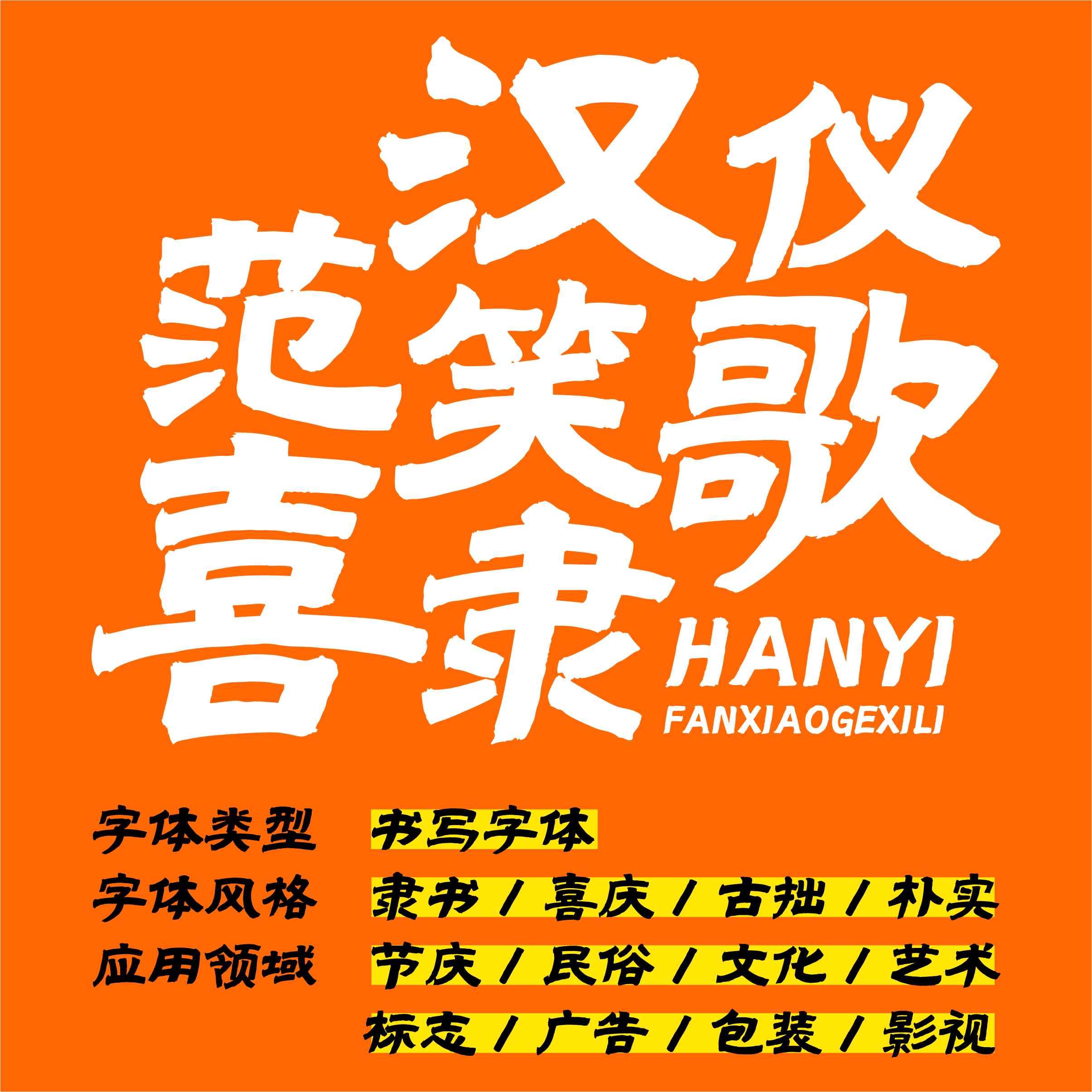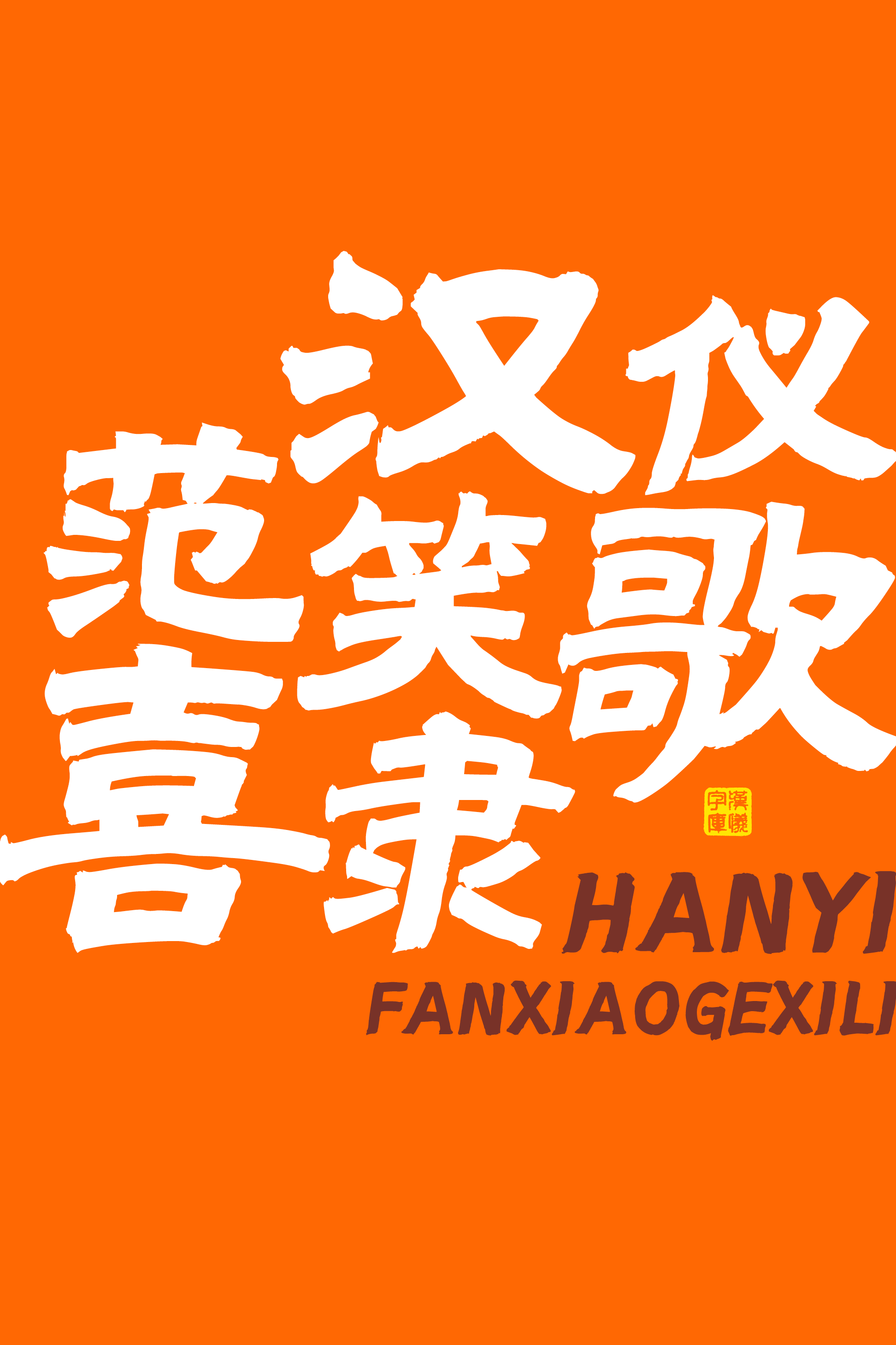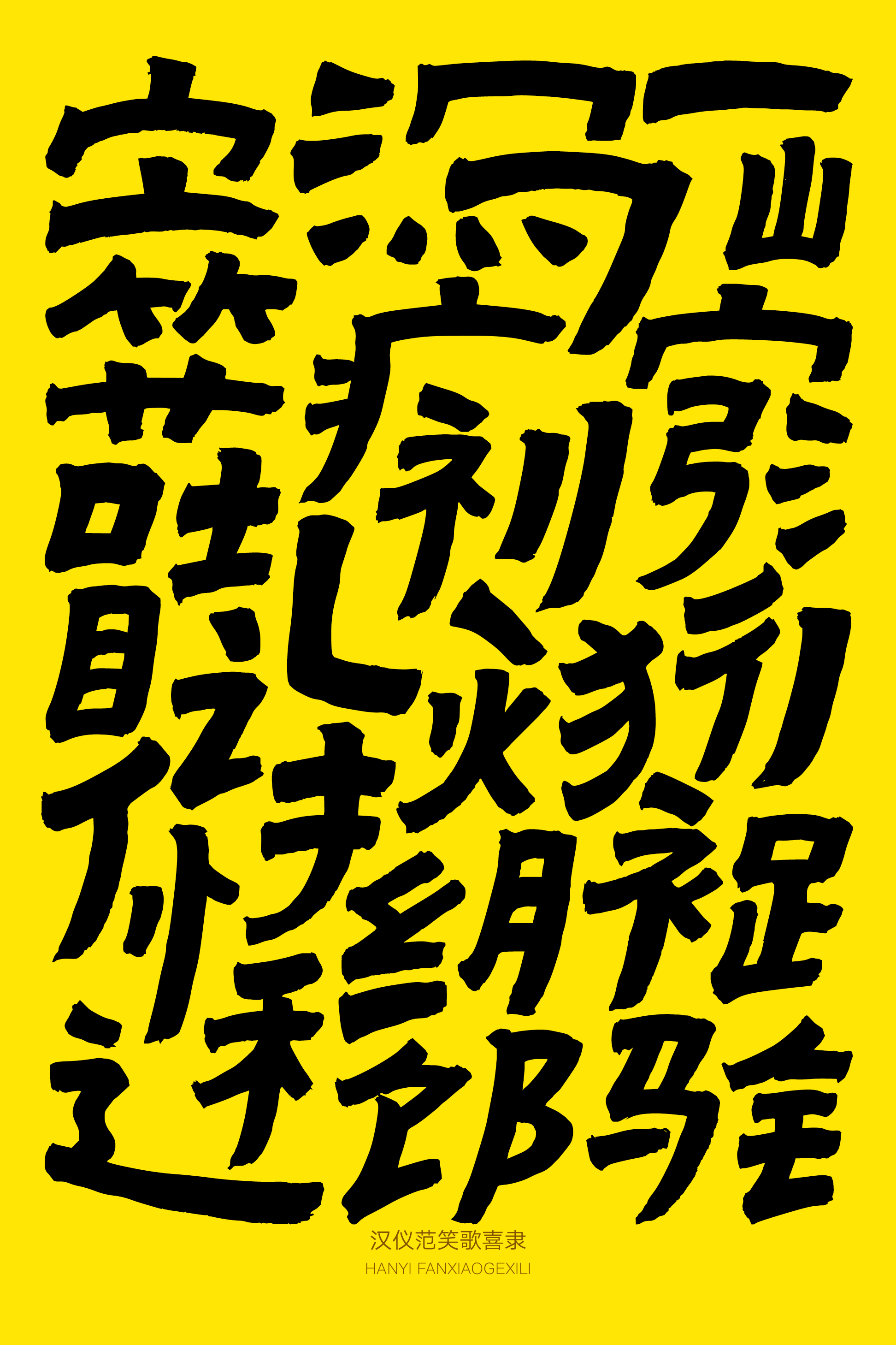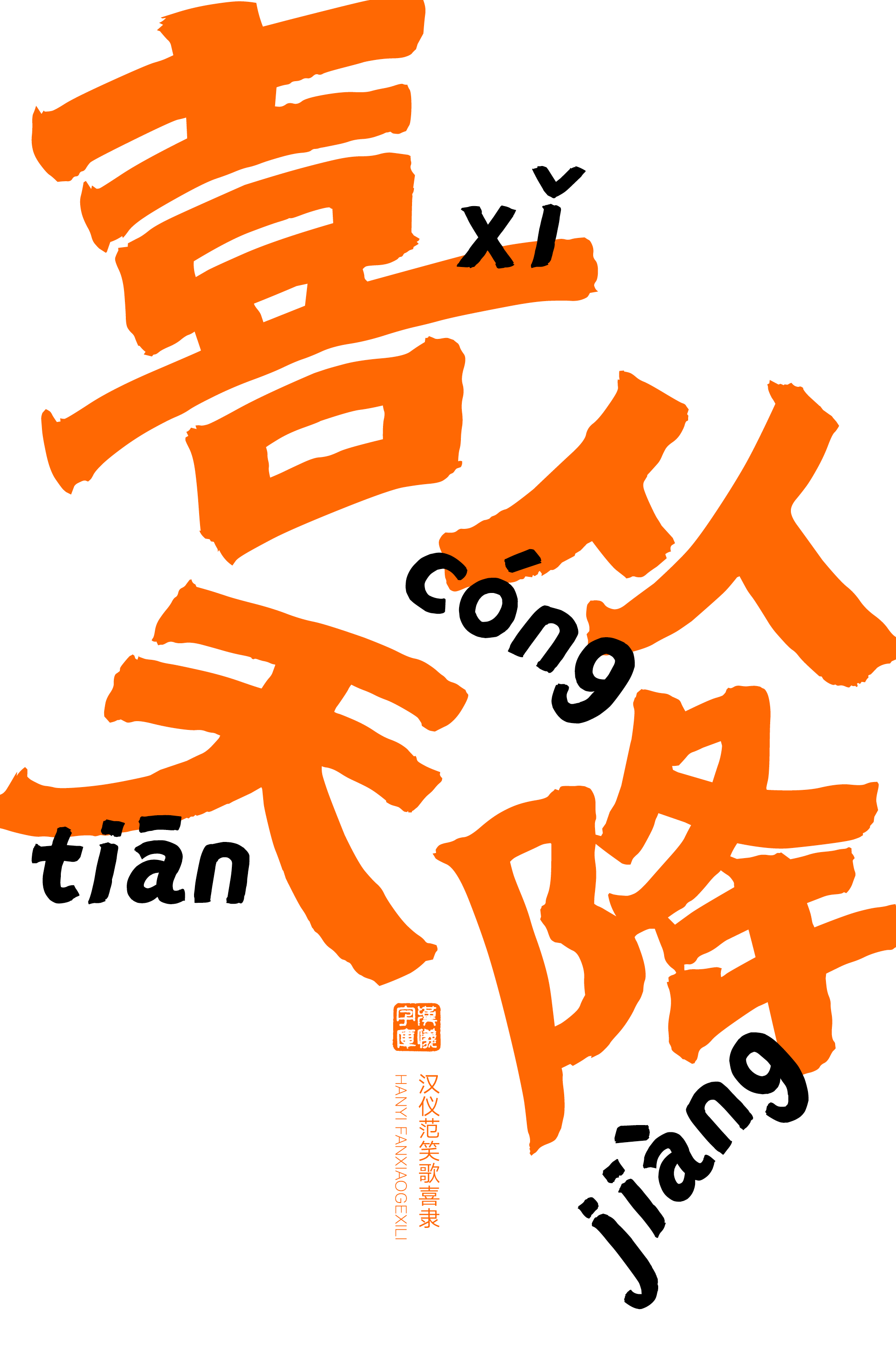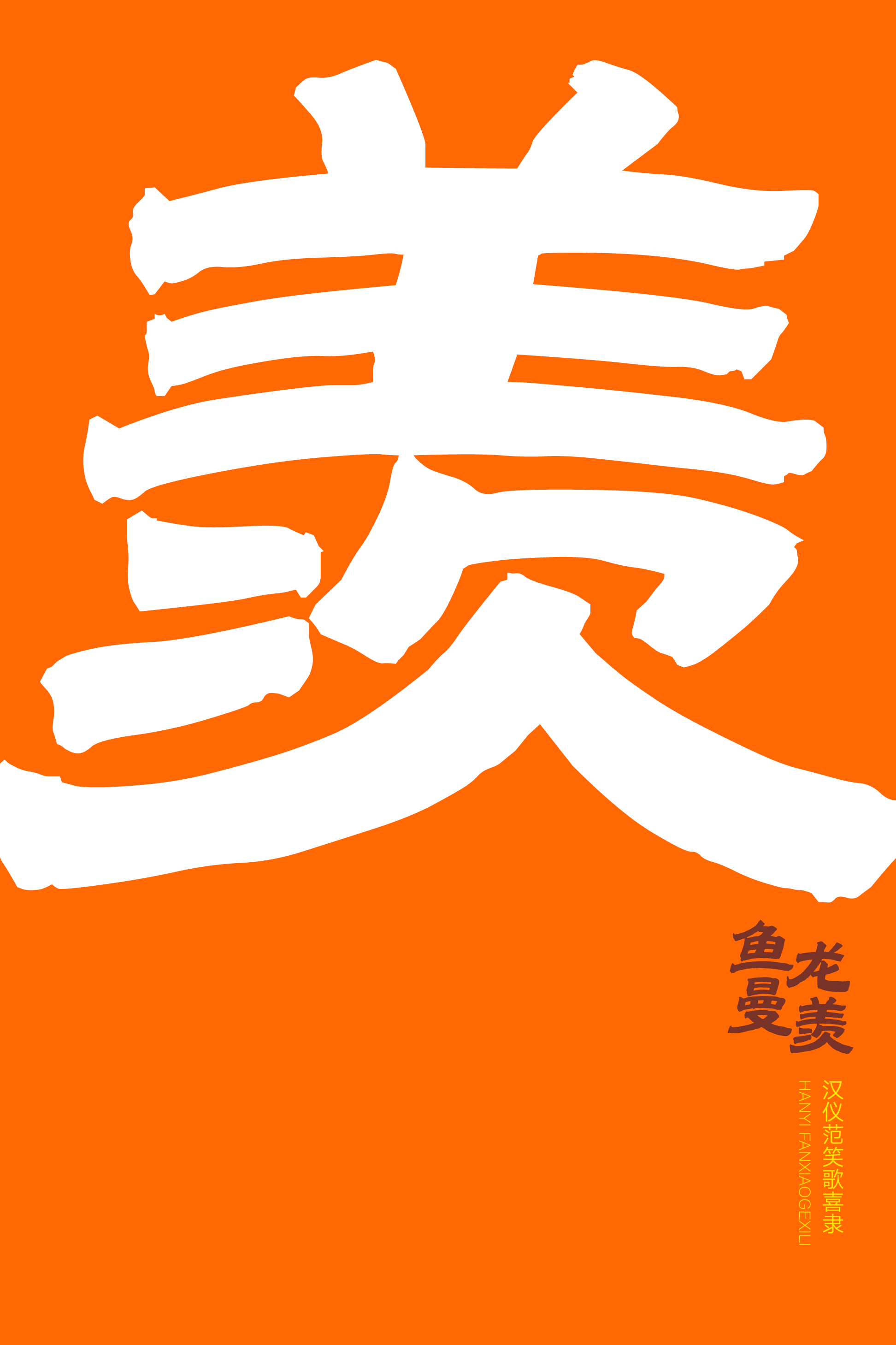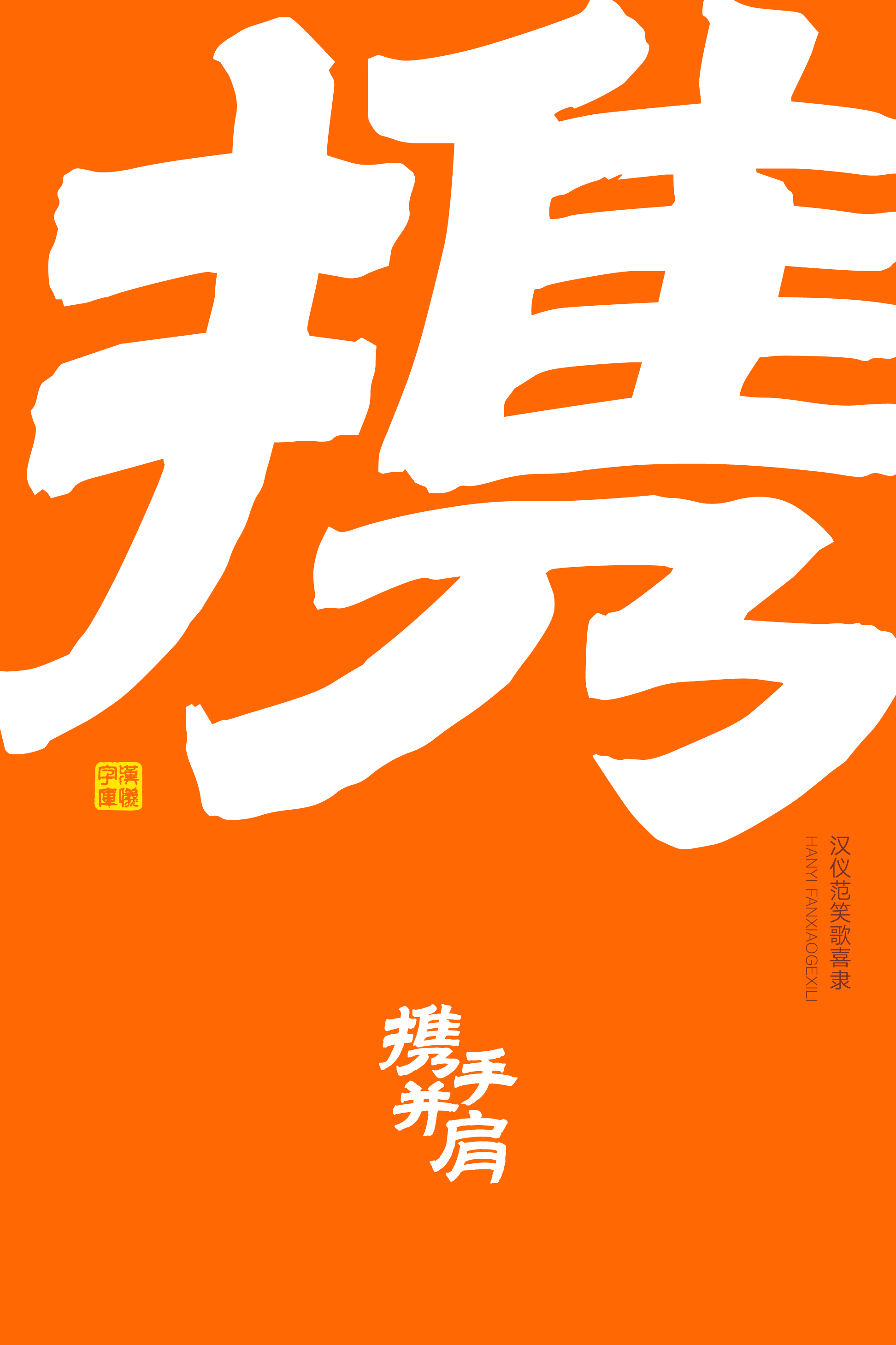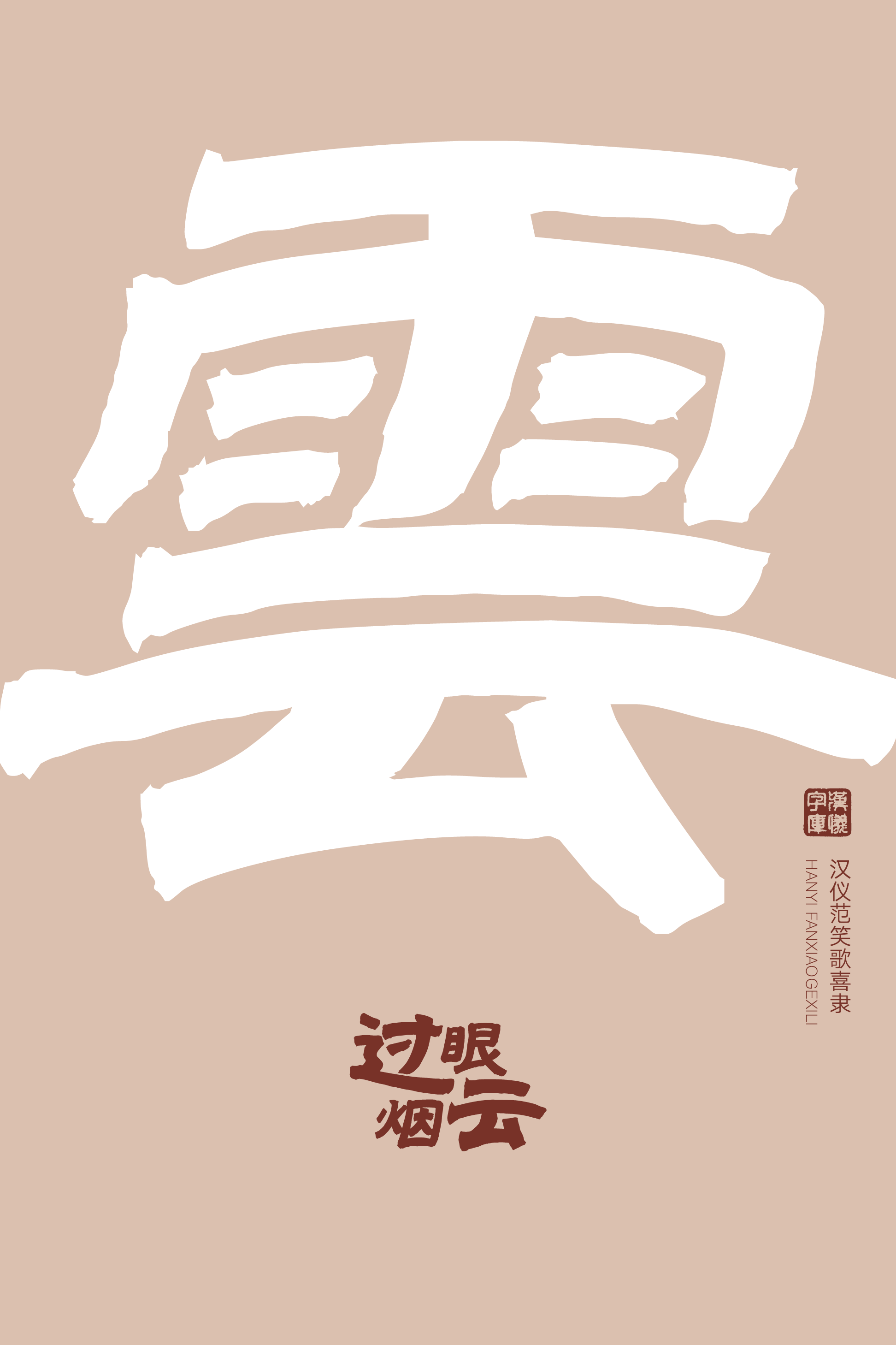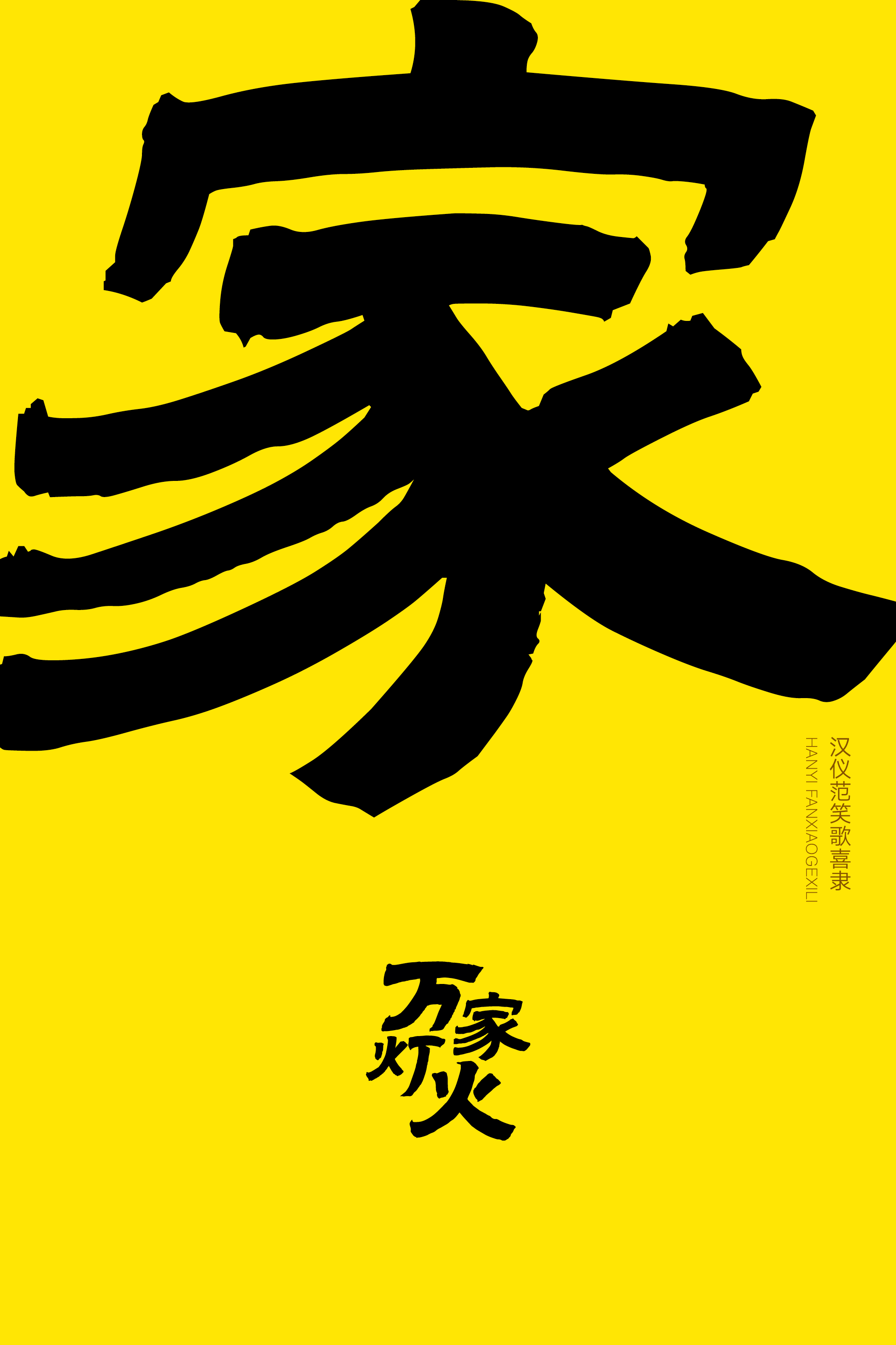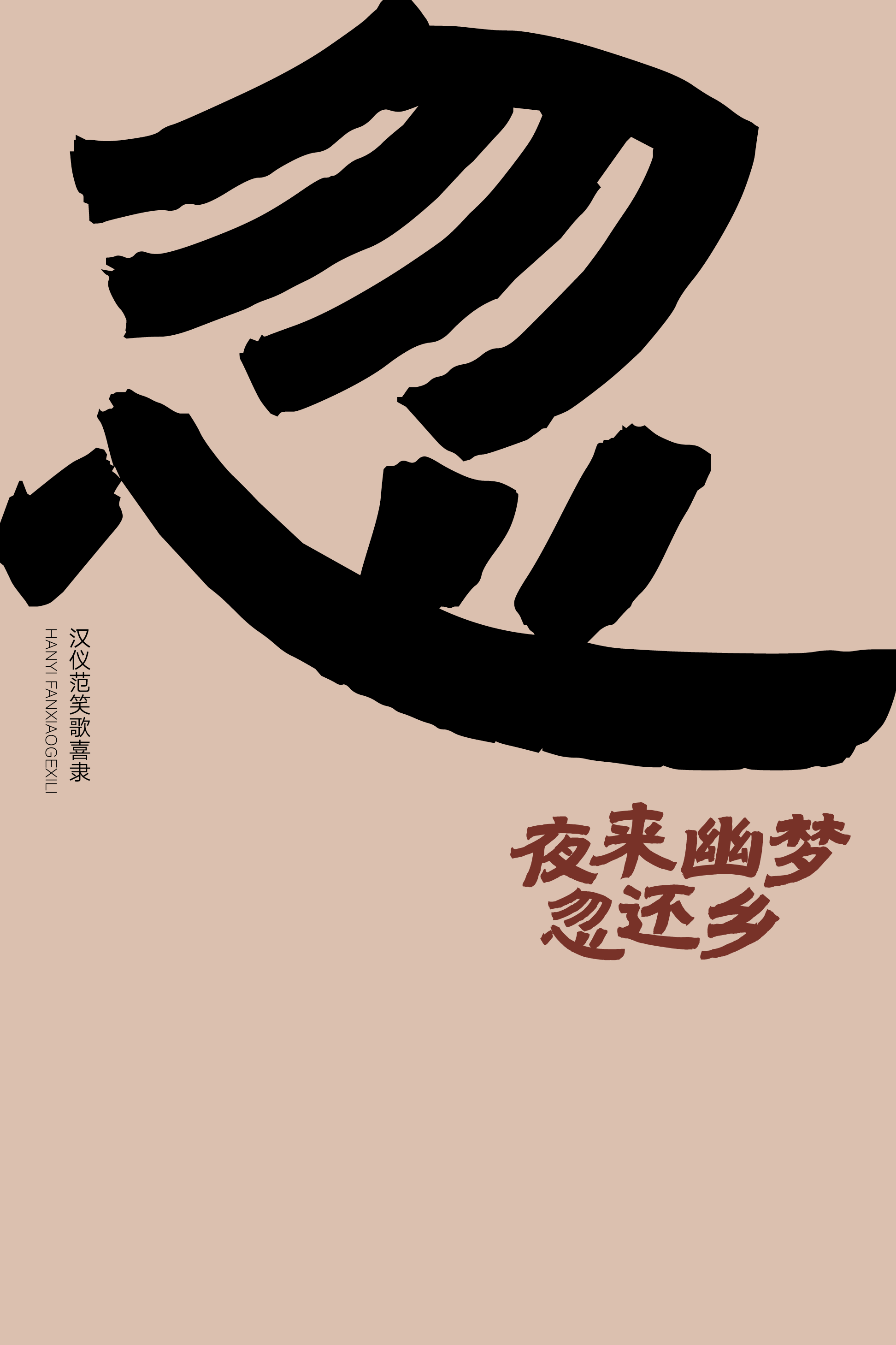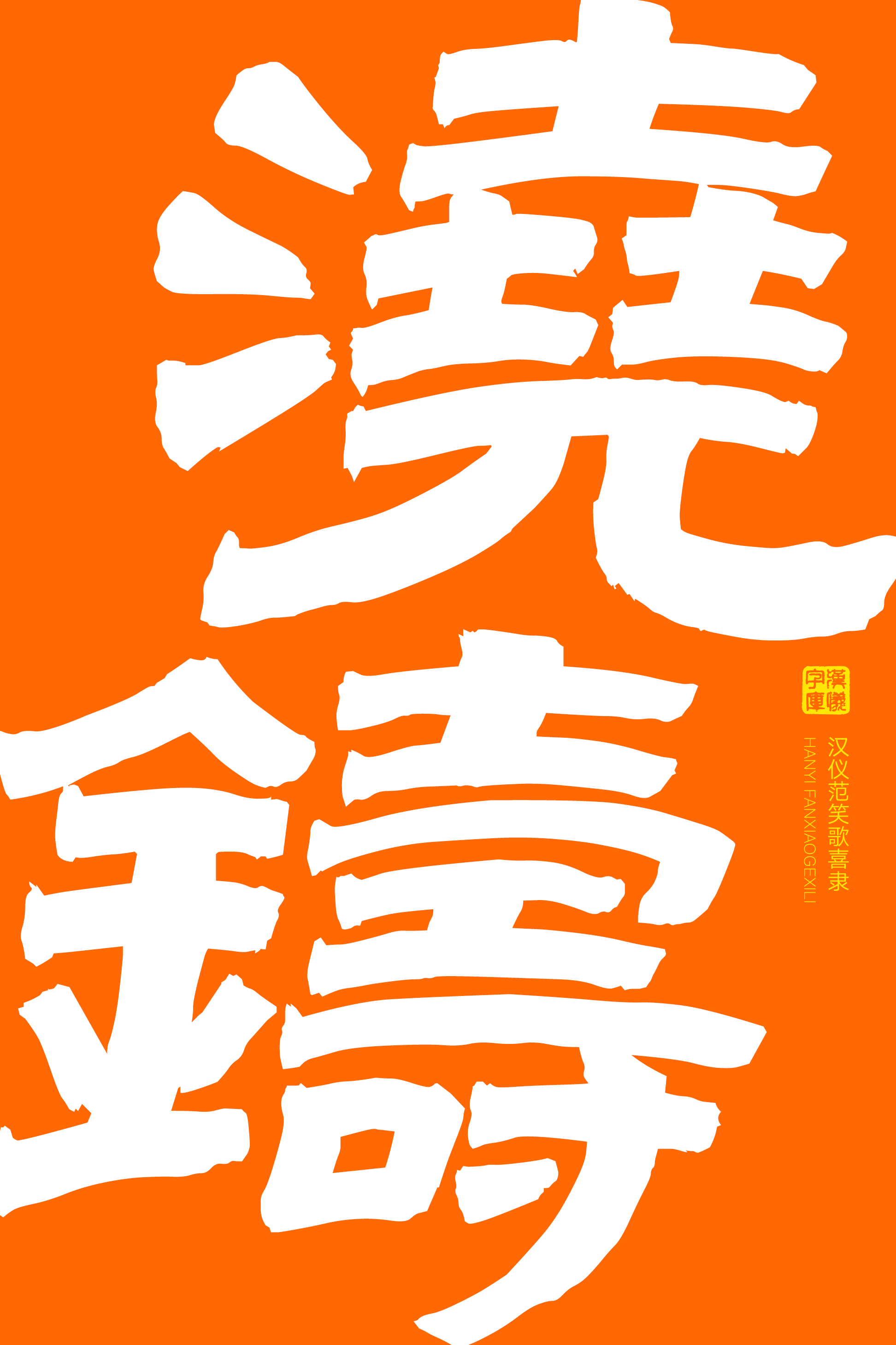
一款喜从天降的隶书
喜从天降——汉仪范笑歌喜隶,喜于形、喜于势,厚重朴实与天然意趣相互平衡。这款书写字体的灵感来源于汉代张迁碑,融合金农隶书的方笔,整体呈扁势,姿态微微倾斜,笔形略有弧度,整体蓄有动态。汉仪范笑歌喜隶适合作为标题字体应用于传统节庆、学术文艺、民俗文化等使用场景,渲染喜乐、淳朴、自然的氛围。
汉仪范笑歌喜隶的书写灵感来源于汉代张迁碑,并融合金农隶书的方笔。
整体取横势,姿态微微倾斜。
以方笔书写,笔形略有弧度而蓄动势。
西文部分同样以方笔书写,保持与中文部分一致的斜势。